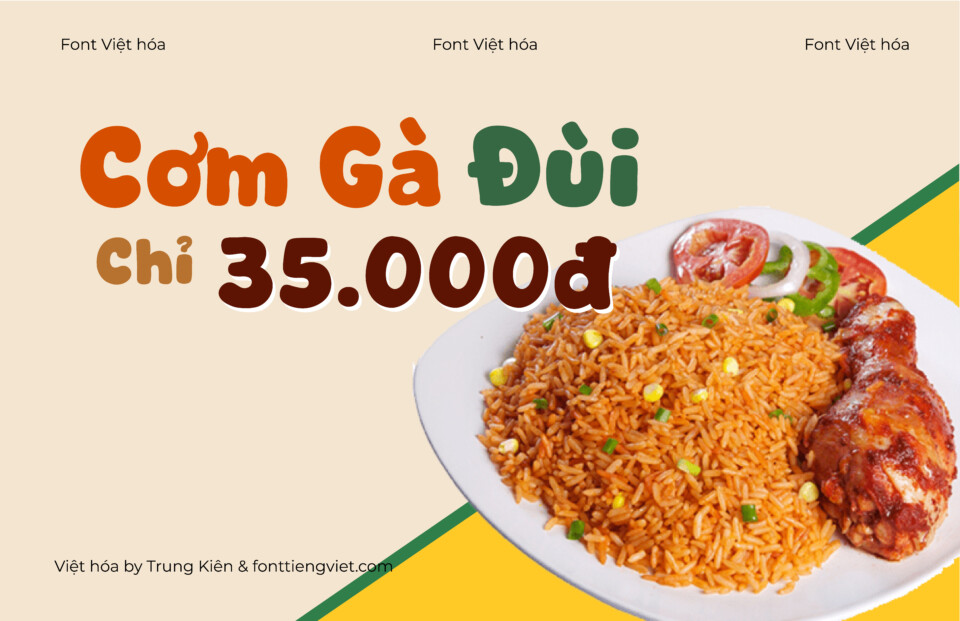
Trong thế giới sáng tạo dành cho học đường, việc lựa chọn một bộ Font Chữ phù hợp đóng vai trò cực kỳ quan trọng để thu hút sự chú ý của các em học sinh. Font Việt hóa 1FTV VIP Cute Dino nổi lên như một lựa chọn hàng đầu nhờ phong cách thiết kế ngộ nghĩnh, lấy cảm hứng từ những chú khủng long đáng yêu. Đây là bộ font được tinh chỉnh kỹ lưỡng, hỗ trợ đầy đủ tiếng Việt giúp các thầy cô và các bạn học sinh dễ dàng tạo ra những bài giảng hay tài liệu học tập sinh động mà không lo lỗi hiển thị.
Đặc điểm nổi bật của Font Việt hóa 1FTV VIP Cute Dino
Thiết kế ngộ nghĩnh và gần gũi
Bộ Font Việt hóa 1FTV VIP Cute Dino sở hữu những đường nét bo tròn, mềm mại và đầy tính nghệ thuật. Hình dáng của từng ký tự gợi liên tưởng đến sự tinh nghịch, giúp giảm bớt sự khô khan trong các văn bản giáo dục thông thường. Điều này đặc biệt hữu ích khi thiết kế tiêu đề cho các bảng tin lớp học hoặc làm nhãn vở cho học sinh tiểu học.
Khả năng ứng dụng đa dạng trong nhà trường
Không chỉ dừng lại ở việc trình chiếu PowerPoint, font chữ này còn rất phù hợp để in ấn trên các sản phẩm quà tặng, thiệp mời sự kiện trường học hoặc trang trí không gian lớp học theo chủ đề thiên nhiên. Sự rõ ràng của các dấu câu trong bản Việt hóa giúp trẻ em dễ dàng đọc hiểu và tiếp nhận thông tin một cách tự nhiên nhất.